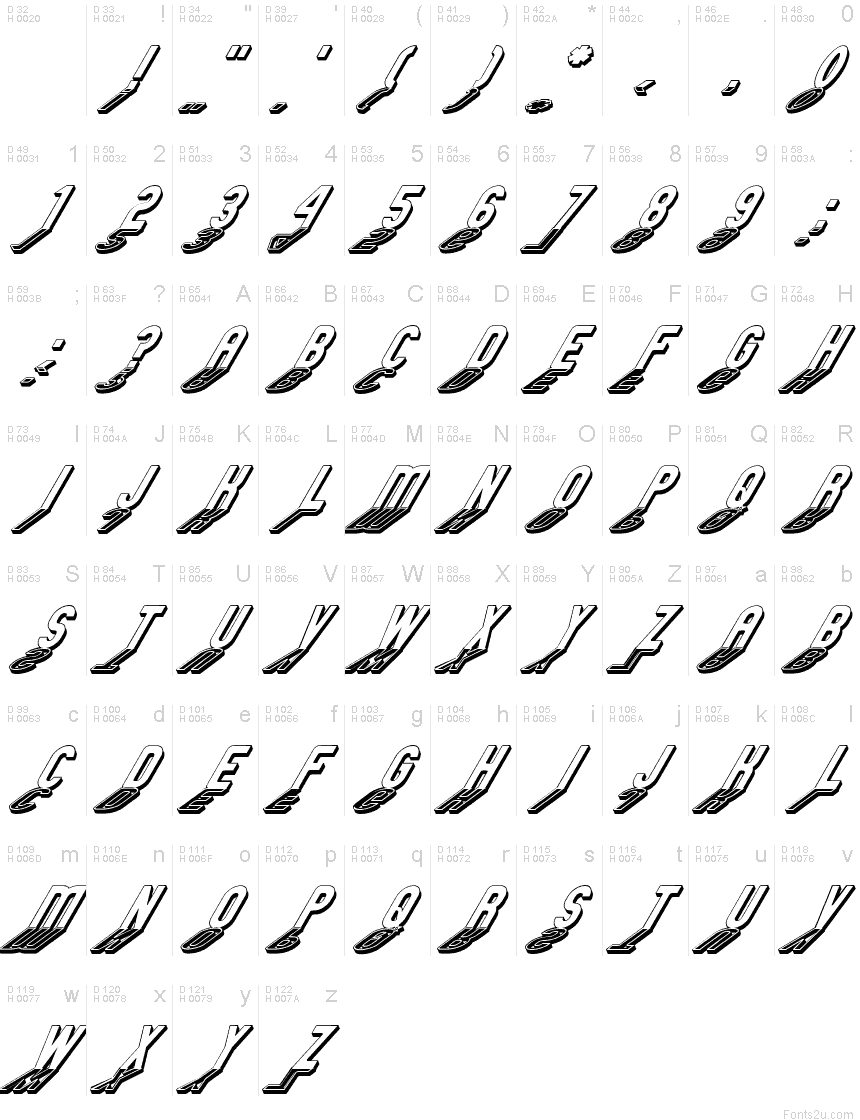
GM Exp Shadow Gravestone2 od G.M. to darmowy krój pisma 3D typu display, który uderza z siłą rozpędzonego napisu tytułowego. Ciężkie, pochylone litery tną przestrzeń, a grube, przesunięte cienie tworzą odważny efekt podwójnej warstwy – niemal jak stos winylowych naklejek zsuwających się z kartki. Ostre krzywizny i ciasny rozstaw nadają mu dynamizmu i charakteru, sprawiając, że każde słowo brzmi głośno, szybko i nieco niepokornie.
Dzięki GM Exp Shadow Gravestone2 nagłówki nie tylko leżą na stronie – one rzucają się w oczy, co sprawdza się idealnie w przypadku plakatów, tytułów gier, logo zespołów, ulotek w klimacie horroru lub punka, oprawy wydarzeń i wyrazistych grafik do mediów społecznościowych. Ten darmowy font najlepiej sprawdza się w dużych rozmiarach; w tekstach głównych połącz go z prostym, neutralnym bezszeryfowym krojem, aby wymiarowy cień pozostał główną gwiazdą Twojego projektu.